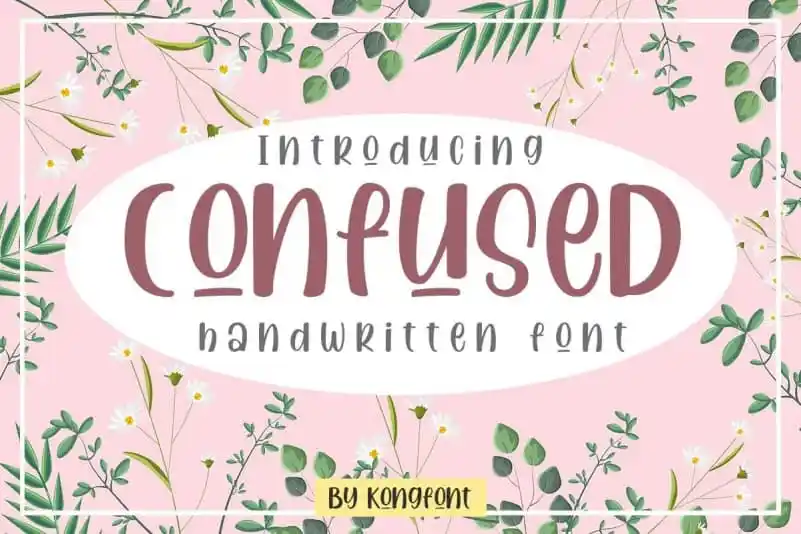
Confused Handwritten Font – Download Grátis
A Confused Handwritten Font é uma escolha perfeita para quem busca uma mistura atrevida e sofisticada nas criações digitais. Esta fonte casual mas elegante é ideal para ambientes de diferentes contextos, desde logotipos até a design das etiquetas, passando por cartões de visita e materiais promocionais. O designer Hamilton criou uma fonte com um visual confuso e divertido que adiciona um toque único aos seus projetos. Ideal tanto para as novas ideias criativas quanto para o próximo projeto da sua empresa, seja ele em logotipos, design de produtos ou até mesmo materiais promocionais. Seja você designer gráfico, publicitário ou empresarial, a Confused Handwritten Font é uma excelente escolha. Suas linhas espessas e elegantes garantem que seu trabalho brilhe quando for exibido em qualquer formato. Aproveite a versatilidade desta fonte para criar designs irresistíveis e inovadores. Com o estilo casual da escrita, ela se destaca perfeitamente em diferentes contextos e tipos de material. Experimente a diferença que esta elegante fonte pode fazer em seus projetos!